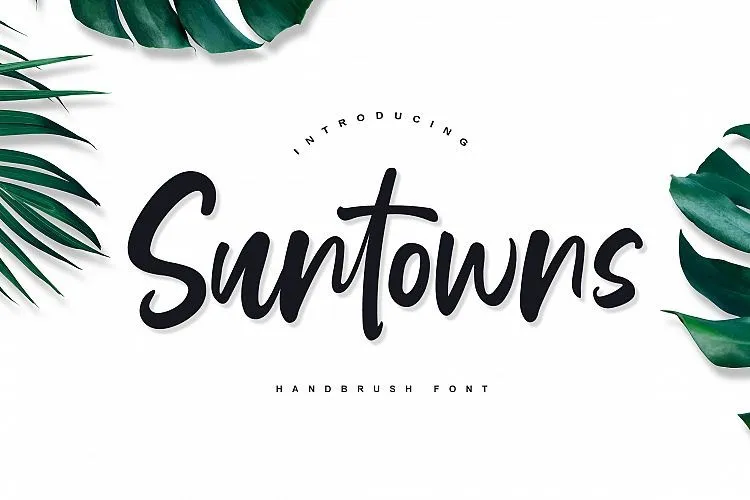
Suntowns Script Font – Download Grátis
Olá amantes do design! Aproveitem a descrição desta fonte script, chamada Suntowns Script Font, criada pelo designer 1001fonts. Essa elegante e delicada fonte é perfeita para todos os projetos gráficos em que você possa precisar de uma letra à mão. Feita com um estilo alegre e natural como se fosse escrita à mão por alguém, a Suntowns Script Font inclui um script curvado divertido e até mesmo uma sans serif toda em letras maiúsculas de um jeito engraçadinho. Ela vai trazer um toque único e prazeroso para qualquer projeto que você estiver realizando. Essa fonte tem um traço suave, feita com cuidado à mão, é perfeita para criação de banners, folhetos, t-shirts impressas, embalagens de marca, cartões de empresa, entre outros. Ela também vem com 50 ligaturas e o símbolo ‘end’ em i,a,u. Esta fonte não só vai lhe ajudar a finalizar seus projetos mais rapidamente, mas você irá sentir uma leveza e naturalidade que se assemelha à letra escrita de maneira delicada. Descubra por si mesmo como essa font se destaca, oferecendo um toque autêntico e natural às suas criações. Tente Suntowns Script Font para dar ao seu trabalho o toque final que ele merece!